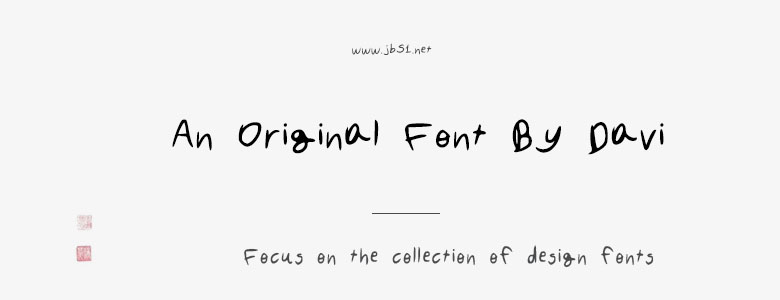
An Original Font By Davi英文手寫字體,字體筆觸纖細(xì),書寫流暢,具有很好的視覺感,適合應(yīng)用于藝術(shù)設(shè)計(jì)、平面宣傳設(shè)計(jì)、網(wǎng)頁(yè)設(shè)計(jì),書法字帖等領(lǐng)域。有需要的朋友快來(lái)本站下載使用吧。